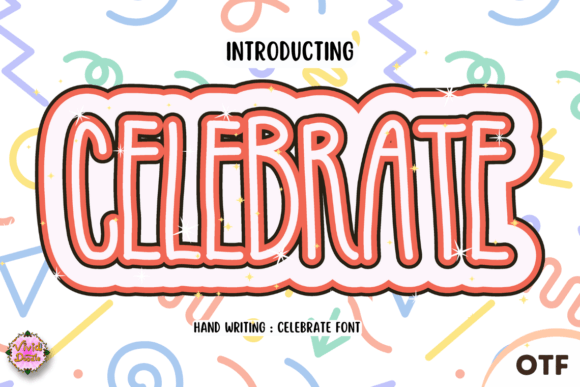
Celebrate
Jika anda sedang mencari aset berkualiti tinggi seperti Celebrate, pakej premium ini merupakan pilihan yang hebat untuk projek kreatif anda.
Sama ada anda mencipta produk POD (Print on Demand), jemputan perkahwinan atau grafik media sosial, Celebrate amat bersesuaian.